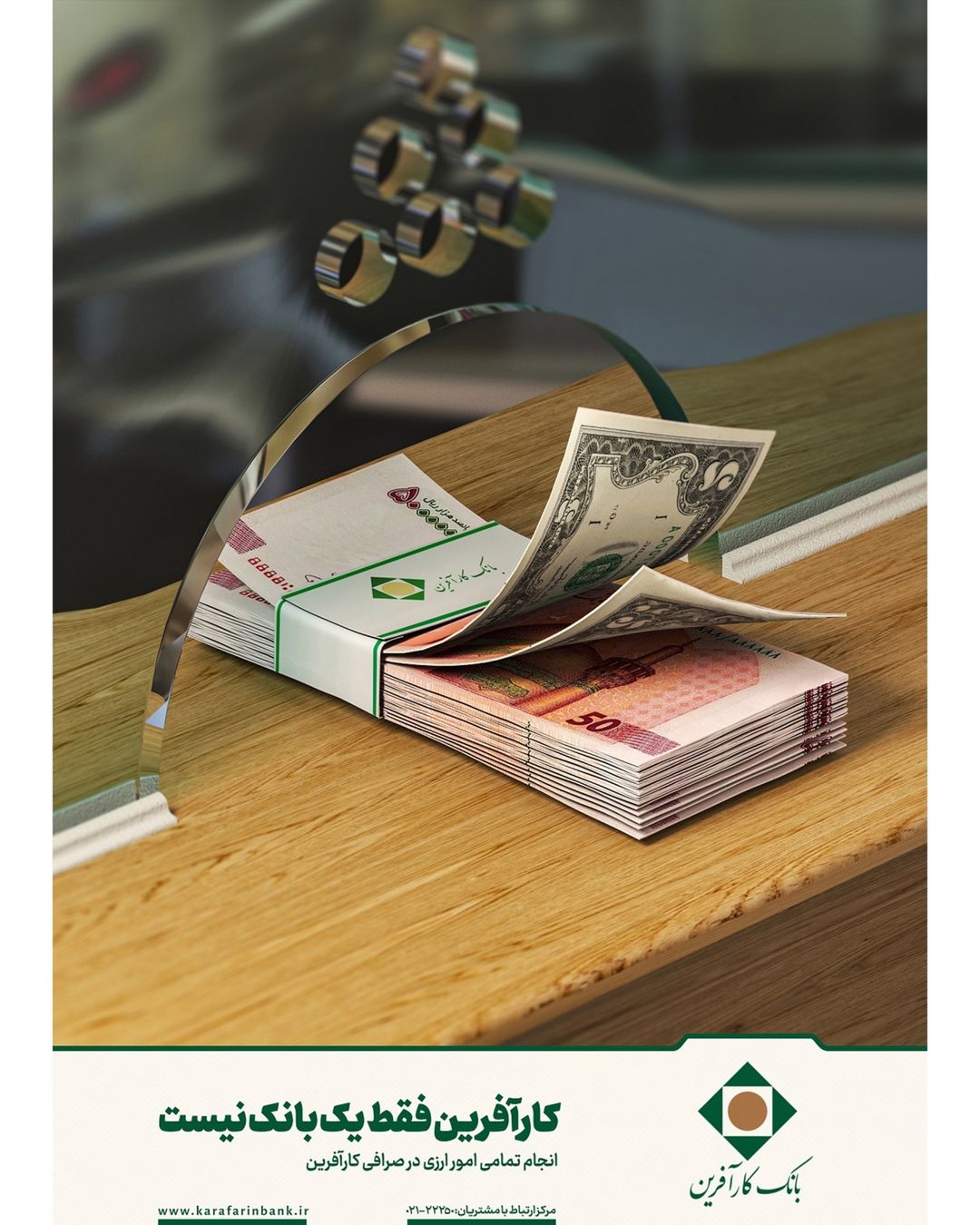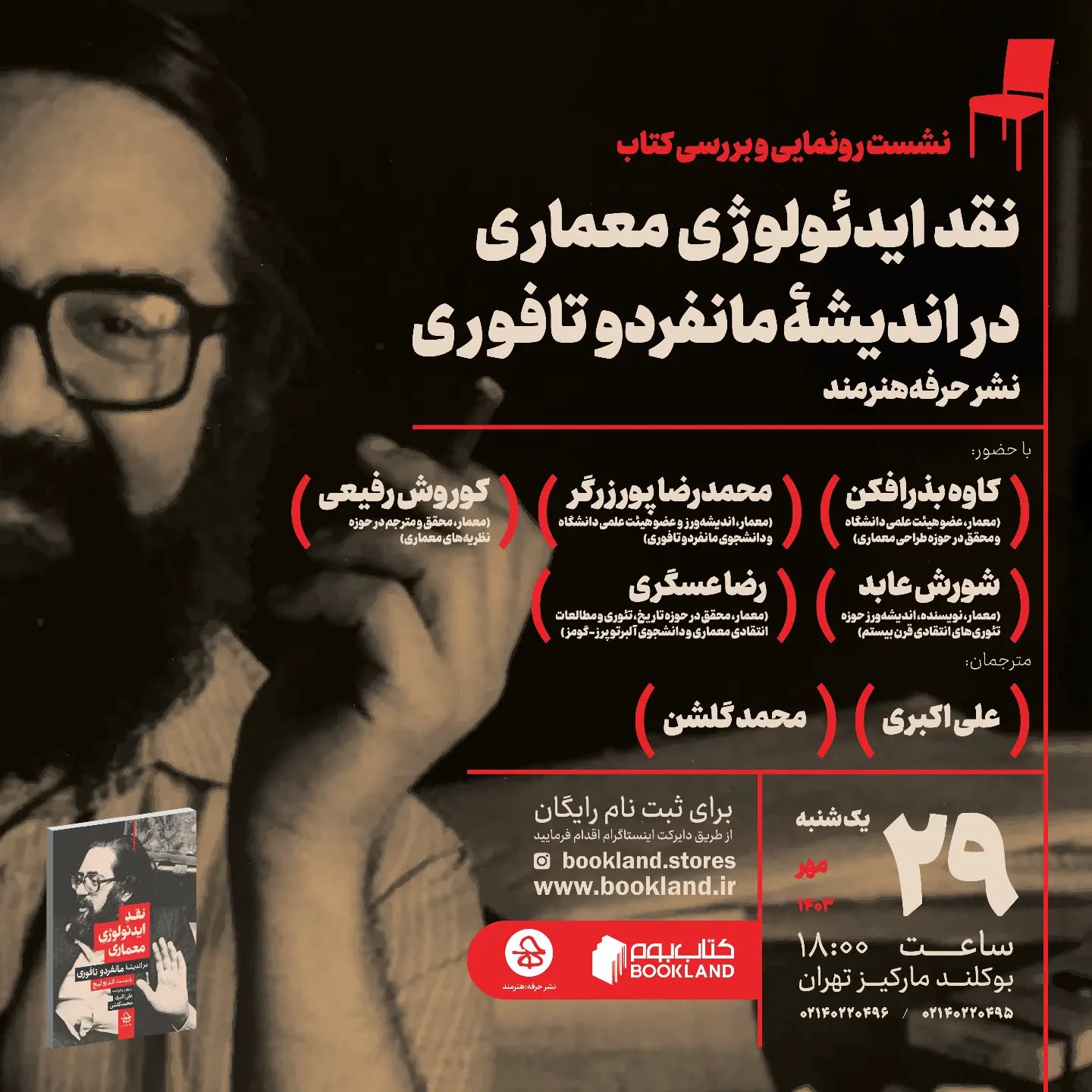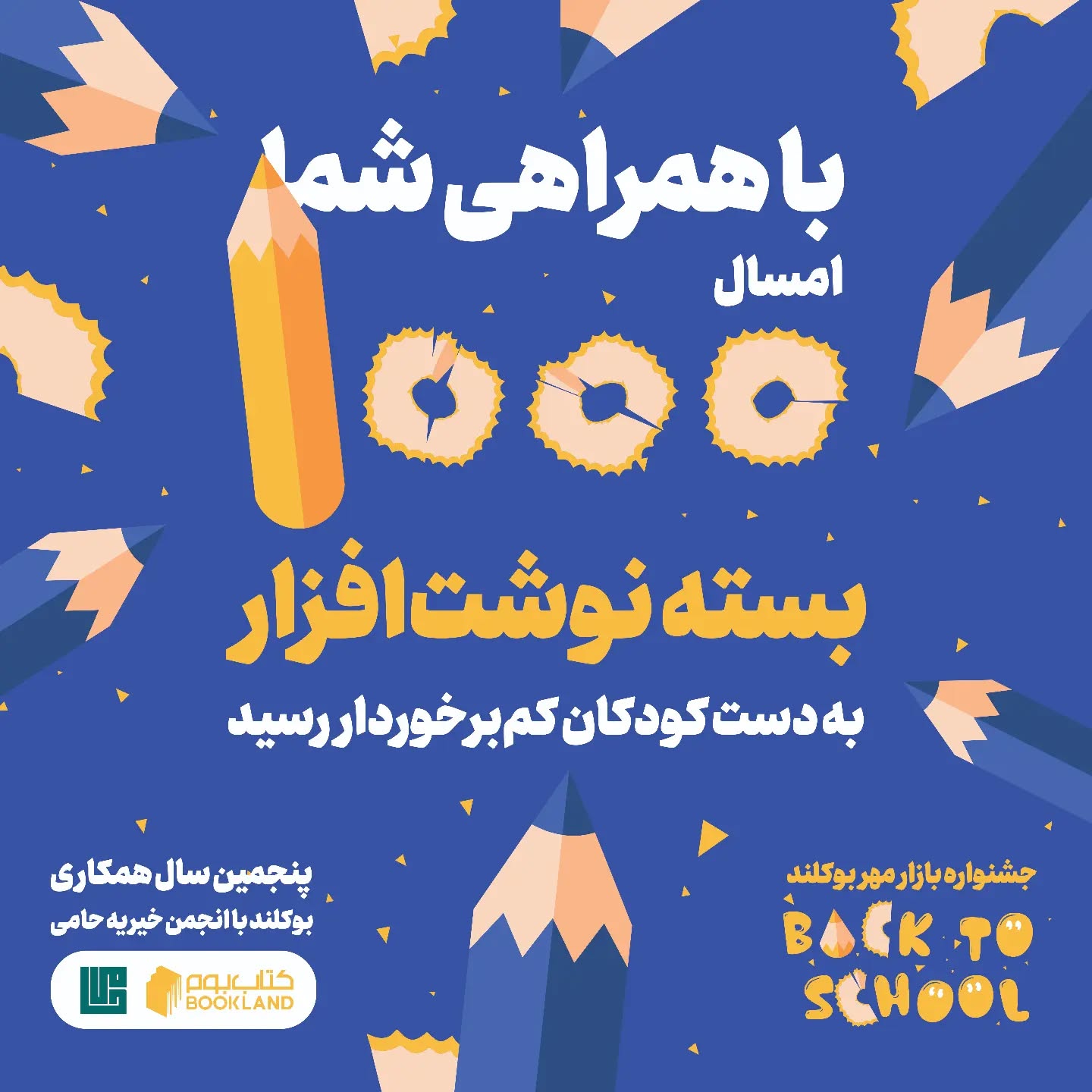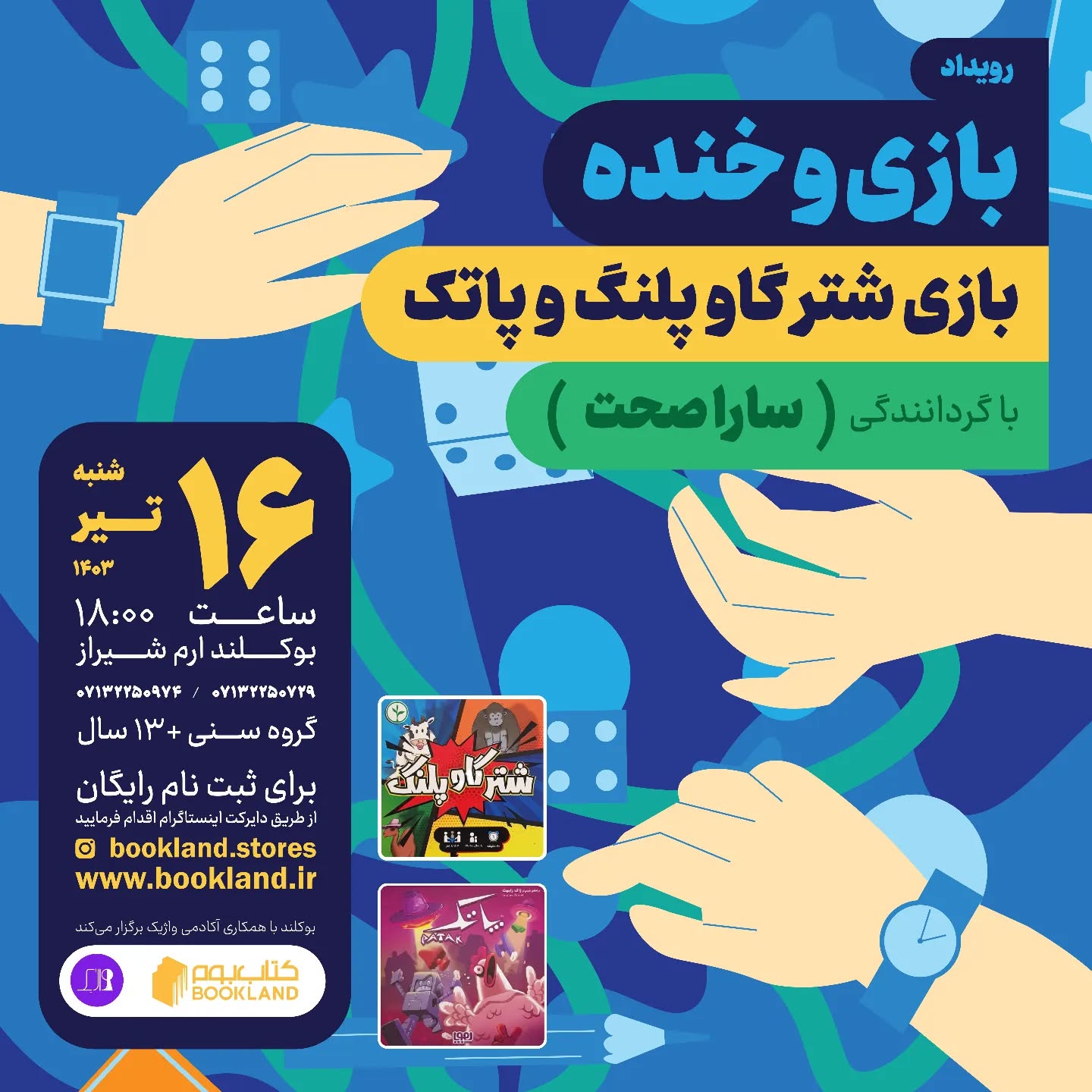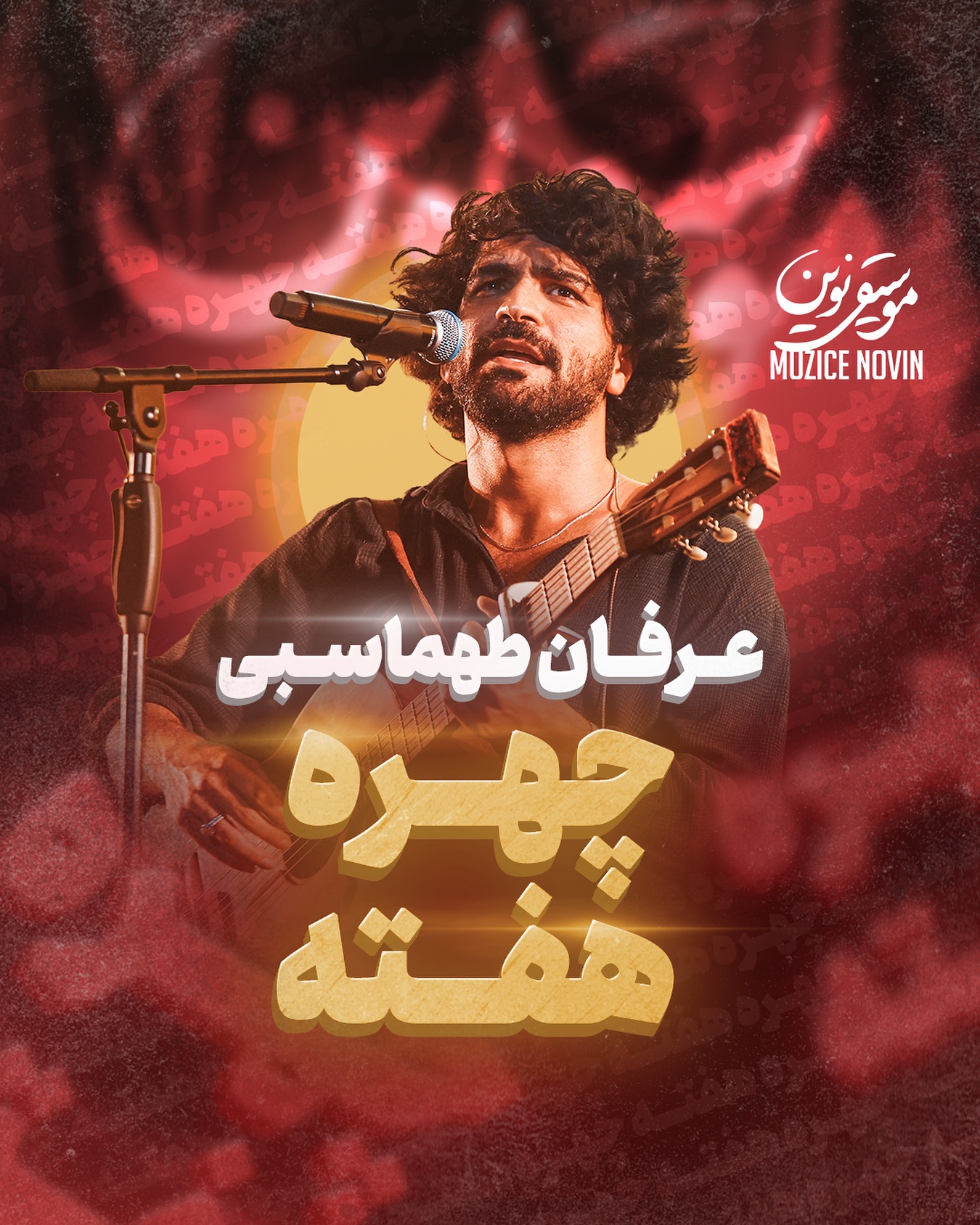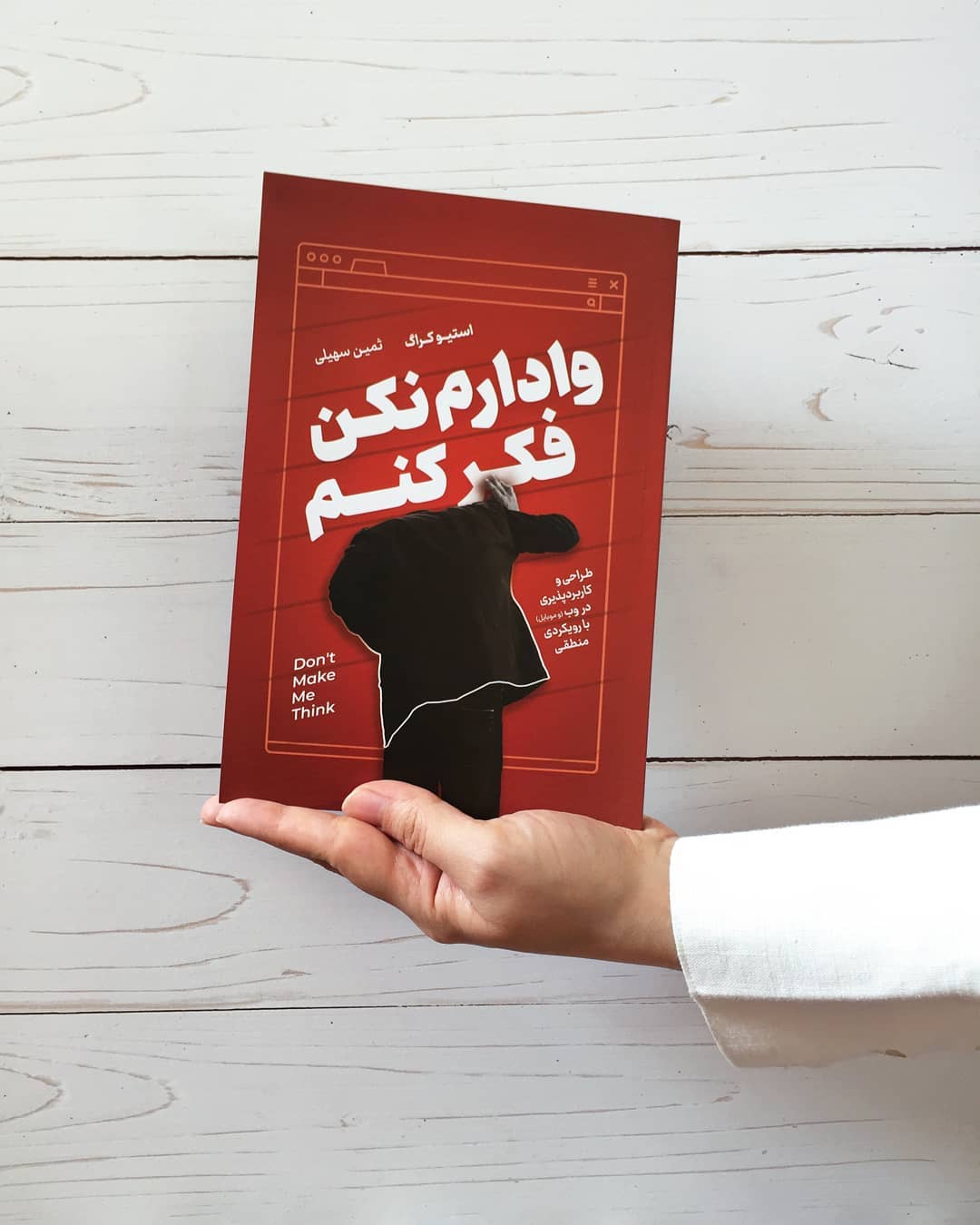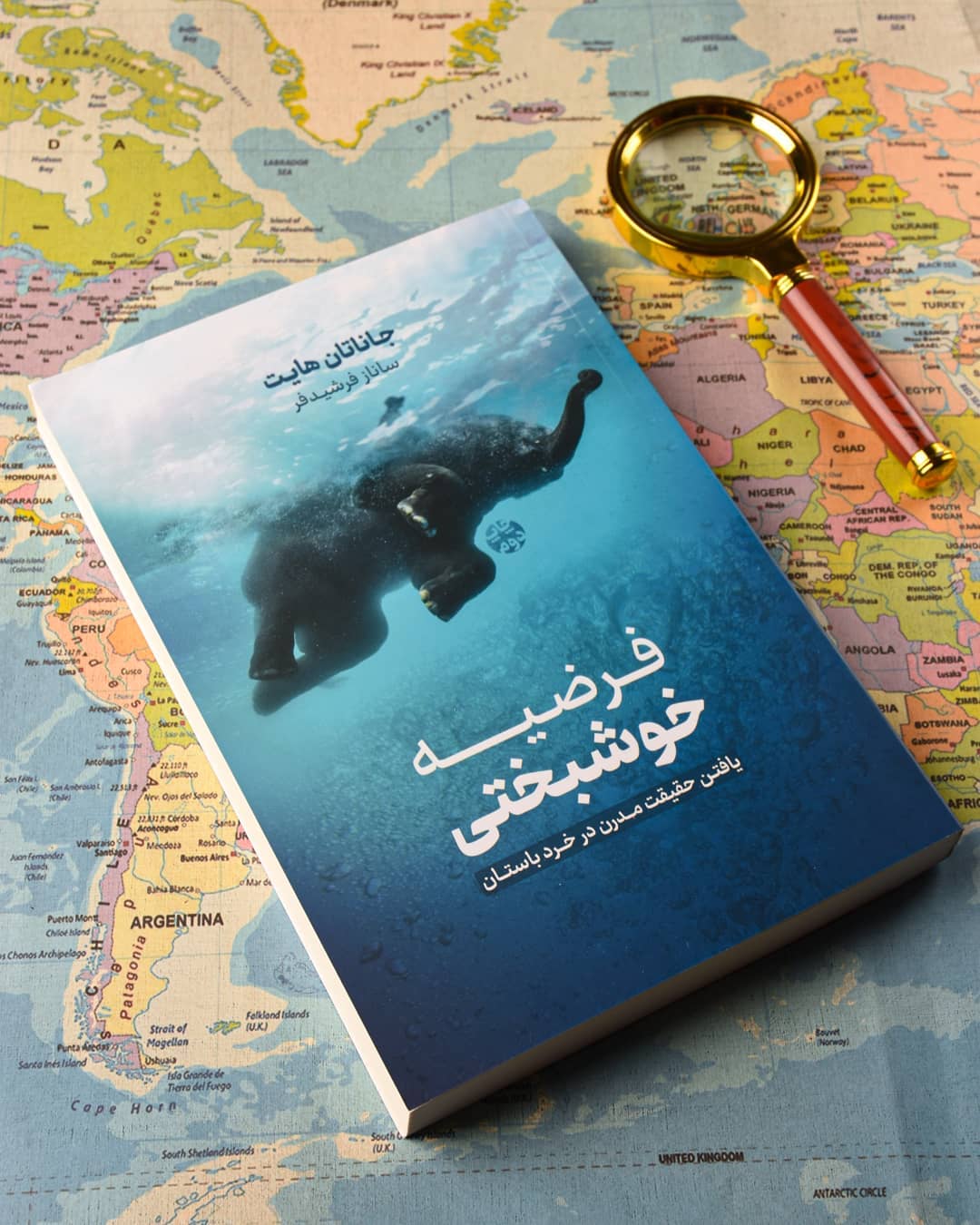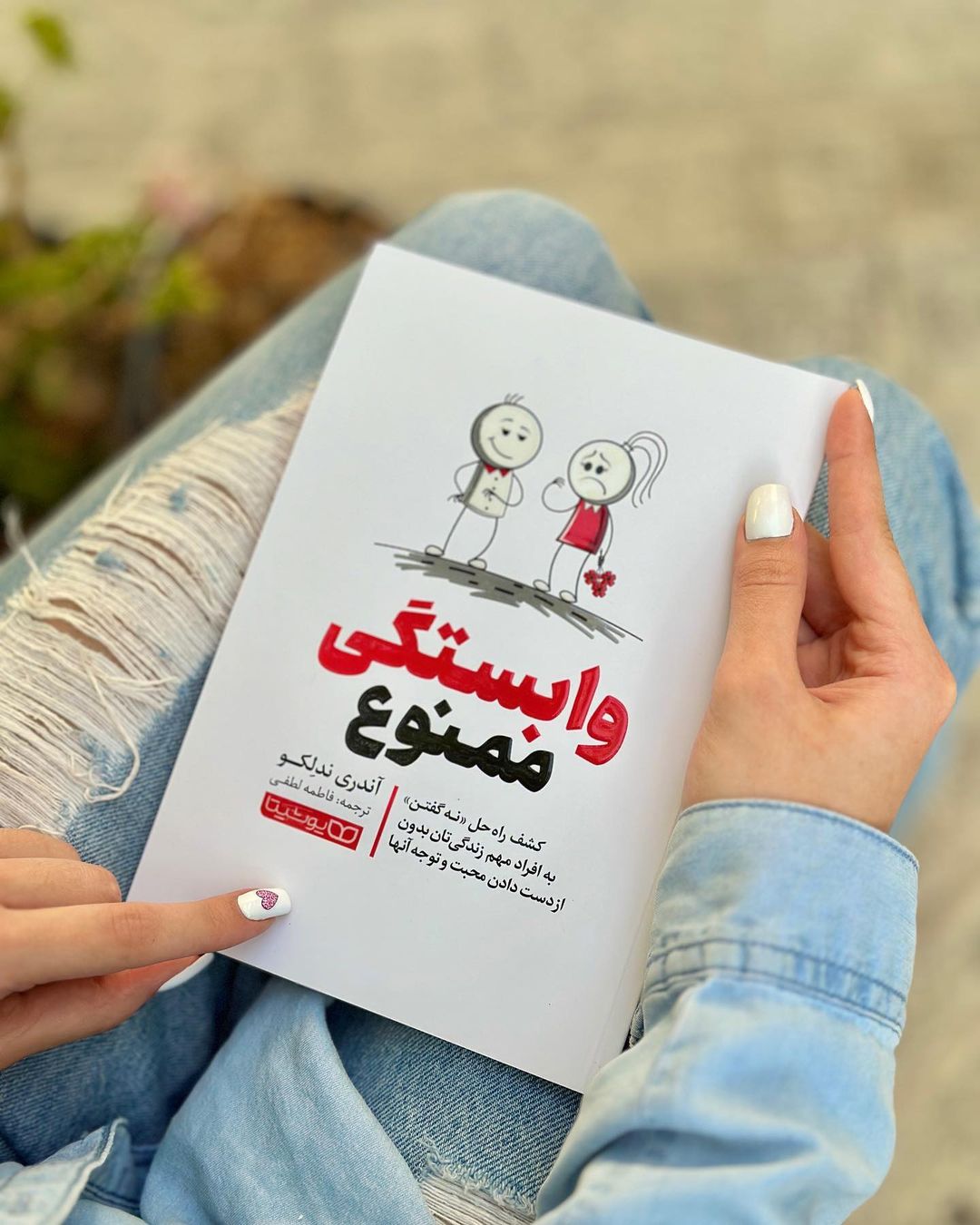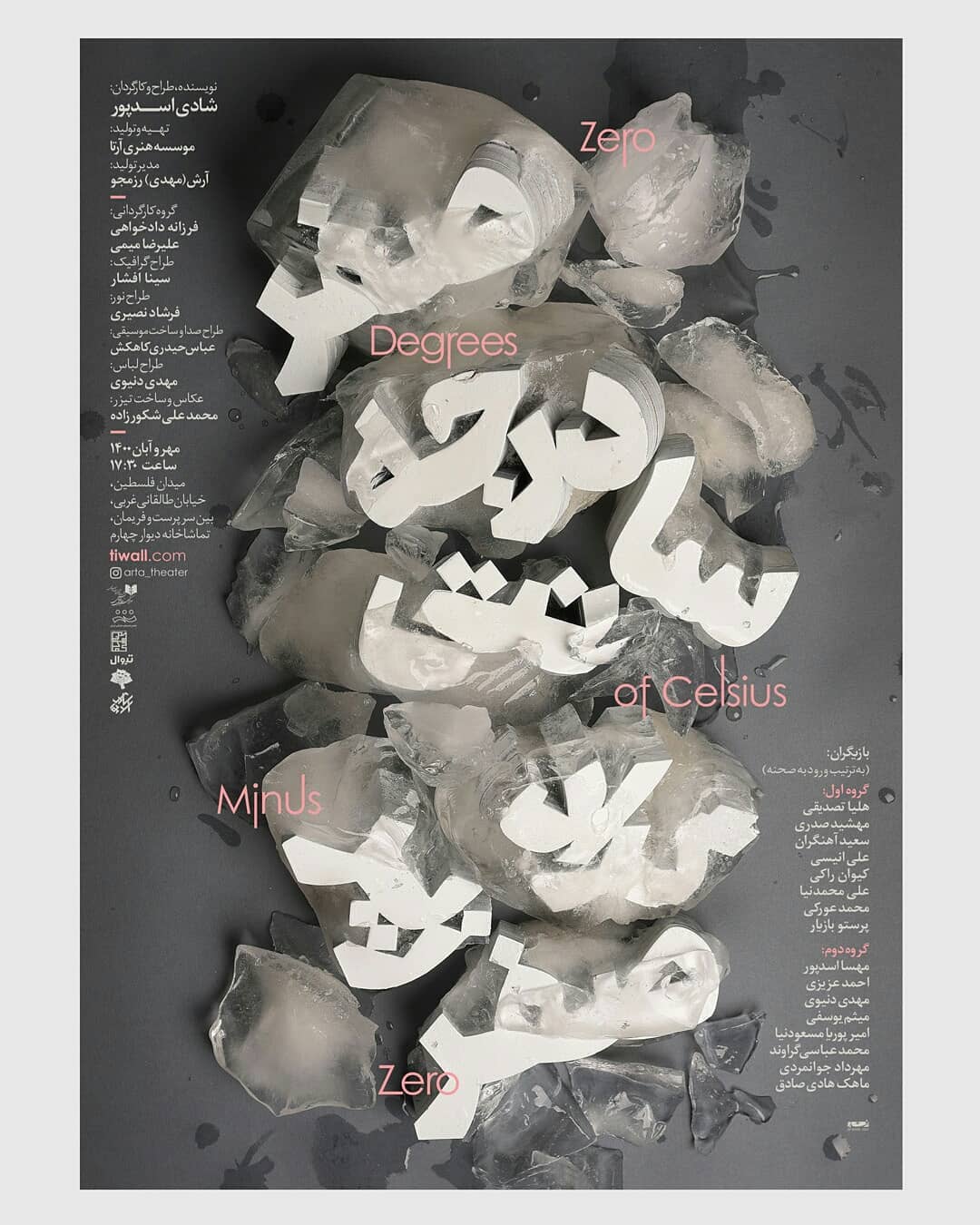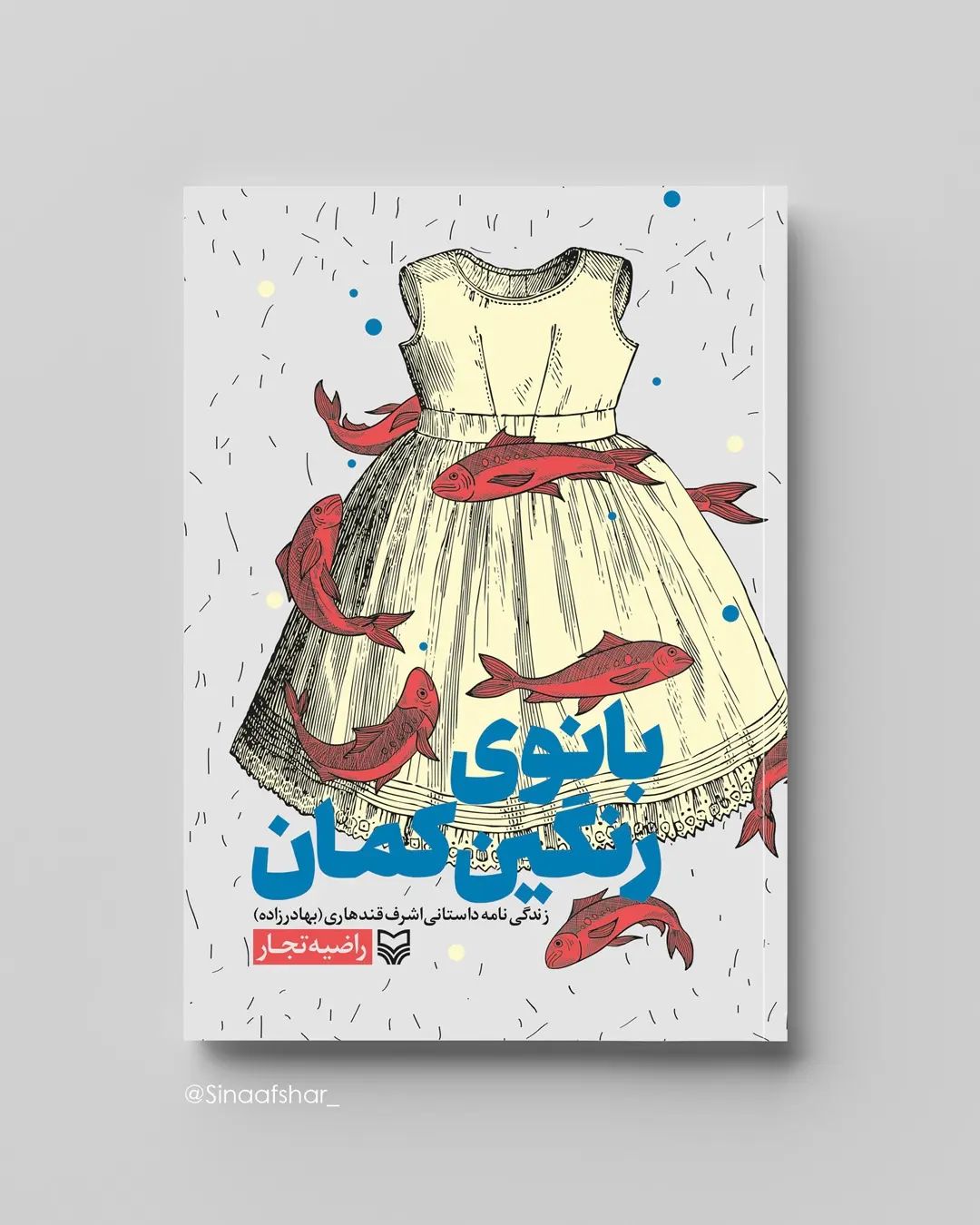
قلم ری font Ray
قلم ری
کاری از امید امامیان و رضا بختیاری فرد
درباره قلم ری
طراحی «ری» با هدف پاسخ‌گویی به نیاز یک فونت جدی و سنگین‌وزن برای کاربردهای تجاری و تبلیغاتی آغاز شد؛ فونتی با استخوان‌بندی محکم و منسجم، فراز و فرودهای کوتاه، سطوح صاف و زوایای متعدد که حضوری قاطع و متمایز در صفحه دارد و توجه مخاطب را به‌سرعت جلب می‌کند.
ری ساده و صریح صحبت می‌کند؛ روراست و منطقی است و اگر چیزی بگوید، می‌توان به آن اعتماد کرد. عمل‌گراست و بی‌واسطه سر اصل مطلب می‌رود. تخصص دارد، با اعتمادبه‌نفس بیان می‌کند و در موقعیت‌هایی که تصمیم‌های بصری باید دقیق و بی‌خطا باشند، قابل اتکاست. همین ویژگی‌ها باعث شده ری نه‌فقط یک انتخاب زیباشناسانه، بلکه یک انتخاب حرفه‌ای و ماندگار باشد.
اکنون بیش از یک دهه از آغاز این مسیر گذشته است. ری در مسیری که برای آن طراحی شده بود درخشید و به‌تدریج از آن فراتر رفت. این تایپ‌فیس در طول این سال‌ها بارها در پروژه‌های بزرگ تجاری، هویت‌های بصری و کمپین‌های تبلیغاتی به‌کار رفته و هنوز هم برای بسیاری از طراحان و مدیران هنری، یکی از اولین انتخاب‌ها به شمار می‌آید.
امروز «ری» علاوه بر دنیای تبلیغات و برندینگ، در حوزه‌های متنوع‌تری حضور فعال دارد و به انتخابی پرکاربرد، کارا و قابل‌اعتماد برای متون مجلات، وب‌سایت‌ها و محصولات دیجیتال تبدیل شده است؛ فونتی که امتحان خود را پس داده و همچنان پاسخ‌گوی نیازهای حرفه‌ای است.
در نسخه‌ی به‌روزشده‌ی «ری»، علاوه بر حفظ شخصیت فرمی و کیفیت‌های بصری اصلی، تمهیدات تازه‌ای نیز لحاظ شده است که باعث می‌شوند این فونت در وب‌سایت‌ها و اپلیکیشن‌ها رفتاری دقیق و قابل اتکا داشته باشد.
تایپ‌فیس «ری» موفق به کسب دو افتخار بین‌المللی شده است:
• دیپلم افتخار مسابقه‌ی Granshan، ۲۰۱۷
• دریافت نشان تایپوگرافی ممتاز از Type Directors Club (TDC)، ۲۰۱۸
در نسخه‌ی ۲ قلم «ری» چه تغییراتی می‌بینیم؟
۱. همه‌ی کاراکترها (حروف، اعداد، علائم، اعراب‌ها و نقطه‌ها) از نظر فرم، ضخامت، اندازه و فاصله‌گذاری بازبینی و اصلاح شدند.
۲. جای اعداد بازبینی شد.
۳. با بازبینی تناسبات و تغییر ارتفاع حروف، ترازبندی عمودی فونت اصلاح شد. حالا قلم در فضای UI کاملاً بی‌دردسر قابل استفاده است.
۴. امکان تغییر تراز عمودی اعداد و علائم مرتبط برای استفاده در UI فراهم شد.
۶. اندازه‌ی قلم ۲۰٪ بزرگ شد.
۷. تقسیم ضخامت بین وزن‌ها کمی تغییر کرد تا قلم کاربردی‌تر شود.
۸. نسخه‌ی وریبل برای قلم ساخته شد.
۱۰. نمادهای «ریال، تومان، ریال عربستان، درهم» برای قلم طراحی شد.
۱۱. فاصله‌گذاری کاراکترهای لاتین بازبینی و اصلاح شد.
۱۲. علائم . : ! ٭ ‘ ’ “ ” « » ‹ › ( ) { } [ ] © ® ™ € ¢ £ ¥ مخصوص کاراکترهای لاتین به قلم اضافه شد.
۱۳. ضخامت و جای Underline و Strikethrough تنظیم شد.
۱۴. فرم «لا» تغییر کرد.
۱۵. مشکل اعراب‌های لله و الله برطرف شد. حالا فقط حرف آخر اعراب می‌گیرد.
ری در کاربرد
طراح قلم
رضا بختیاری فرد
تایپوگرافر و مدرس طراحی تایپ‌فیس و لوگوتایپ
تجربه‌های کاری
• طراحی قلم‌های ایرانسل، ابَر، پیکان، لیلا، باغ کتاب تهران و راوی
• طراحی قلم‌های مای‌بیبی، علی‌بابا، اینورس، بانک آینده، بنیاد کودک و فانوس با همکاری مهدی ارشادی
• طراحی قلم‌های میکا، ری، بانک سپه، واضح و دبستان با همکاری امید امامیان
• طراحی قلم «دوران» با همکاری فرشته ایرانشاهی
• طراحی قلم «نیان» با همکاری افسانه سالک